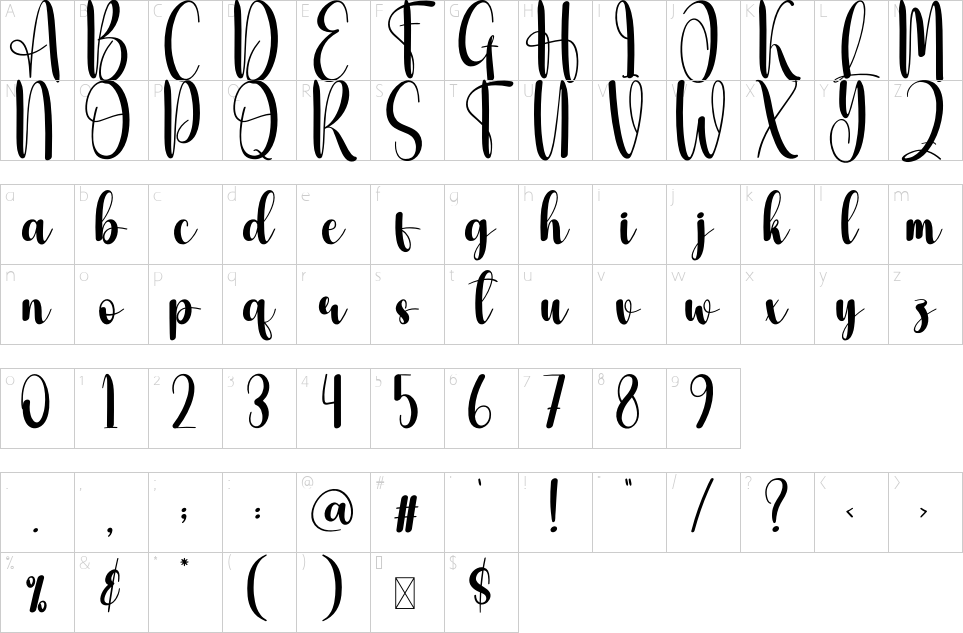
A fonte Mermaid oferece um toque de magia e elegância para seus projetos digitais. Desenhada pelo artista William Jhordy, essa fonte é uma delícia para trabalhar, especialmente em projetos gráficos que valorizam a simplicidade e a seriedade de um traço elegante. Com o Mermaid, você pode criar uma tipografia que não apenas chama a atenção, mas também transmite um sentimento de tranquilidade e elegância. Esta fonte foi popular o suficiente para ter sido baixada 262 vezes, e agora você pode fazê-lo seu, sem pagar nada. Que tal dar uma chance a essa fonte de graciosidade?